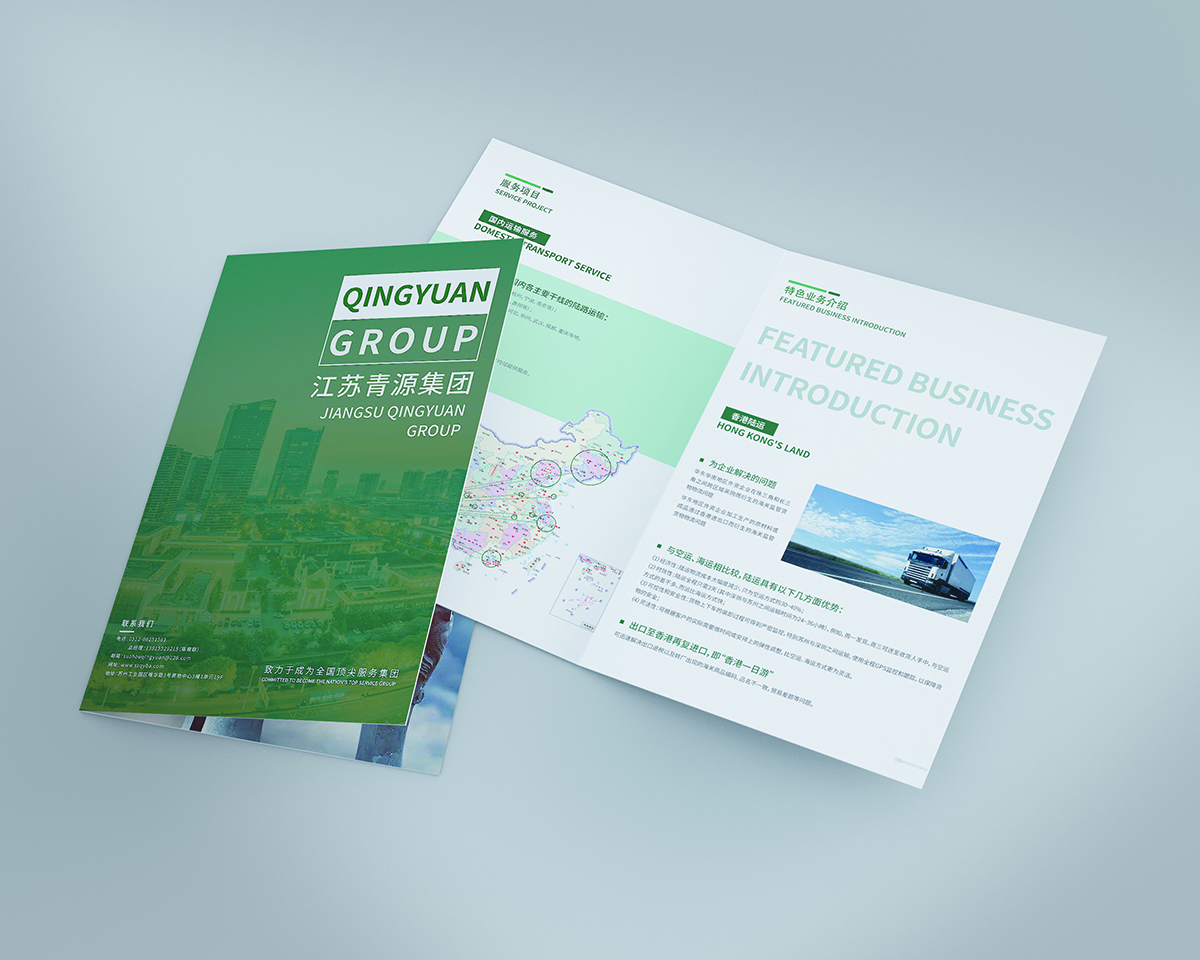
引言
字体在品牌设计中扮演着至关重要的角色,它可以传达品牌的个性、价值观和信息。精心挑选并使用字体可以帮助企业建立强大的品牌标识,提升品牌知名度,并与目标受众建立联系。
字体如何建立品牌标识
以下是如何通过字体建立品牌标识的一些方式:
- 传达品牌个性:不同的字体风格可以传达不同的情绪和特征。例如,衬线字体通常显得优雅和传统,而无衬线字体则显得现代和简洁。
- 建立品牌识别:独特的字体可以帮助品牌在市场中脱颖而出并建立品牌识别。例如,可口可乐的标志性字体“Spencerian Script”已成为其品牌身份不可或缺的一部分。
- 促进品牌忠诚度:一致的字体使用可以建立品牌忠诚度。当消费者在不同的渠道看到相同的字体时,他们会将该字体与品牌联系起来并产生积极的情感。
选择字体的原则
在选择字体时,需要考虑以下原则:
- 品牌个性:字体应该与品牌的个性和价值观相匹配。
- 受众群体:字体应该吸引品牌的目标受众。
- 易读性:字体应该易于阅读,尤其是在较小的尺寸下。
- 可扩展性:字体应该适合在不同的媒体平台和尺寸上使用。
使用字体的最佳实践
以下是使用字体时的最佳实践:
- 一致性:在所有品牌接触点(例如网站、社交媒体和印刷材料)中使用一致的字体。
- 对比度:使用对比鲜明的字体颜色和背景颜色,以提高可读性。
- 层次结构:使用不同大小和样式的字体来创建内容层次结构,使其易于扫描。
- 简洁性:避免使用太多不同的字体。少即是多。
- 专业性:选择专业的字体,避免使用装饰性字体或脚本。
字体对不同行业的品牌标识的影响
字体在不同行业中对品牌标识的影响也各不相同,例如:
- 奢侈品:奢侈品品牌通常使用衬线字体来传达优雅和精致。
- 科技:科技品牌通常使用无衬线字体来传达现代和创新。
- 教育:教育机构通常使用易读的衬线字体来传达权威和可靠性。
- 零售:零售品牌通常使用吸引眼球的无衬线字体来脱颖而出。
结论
字体是品牌设计中必不可少的元素,它可以建立强大的品牌标识,提升品牌知名度,并与目标受众建立联系。通过仔细选择和使用字体,企业可以创造一个独特的和令人难忘的品牌体验,在竞争激烈的市场中脱颖而出。